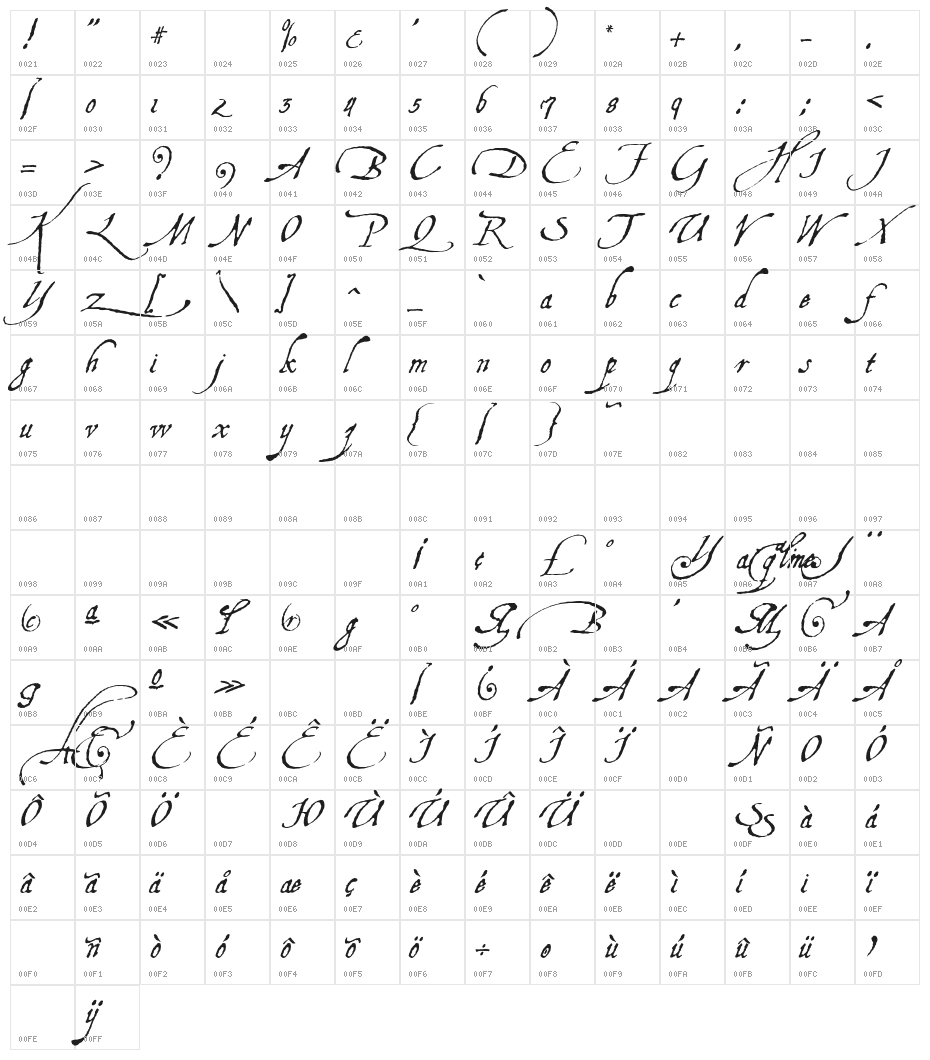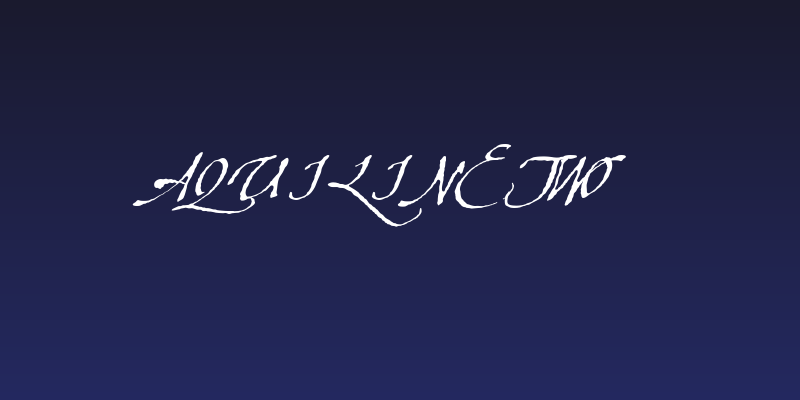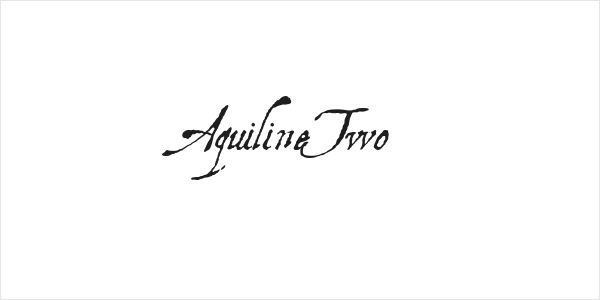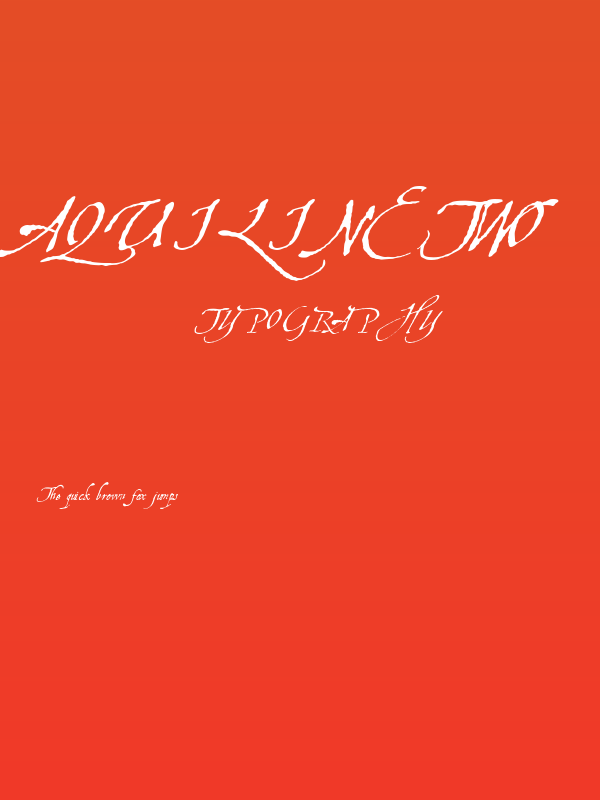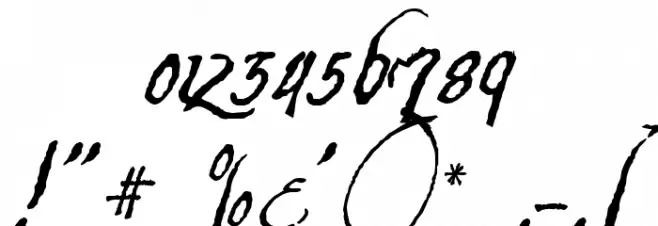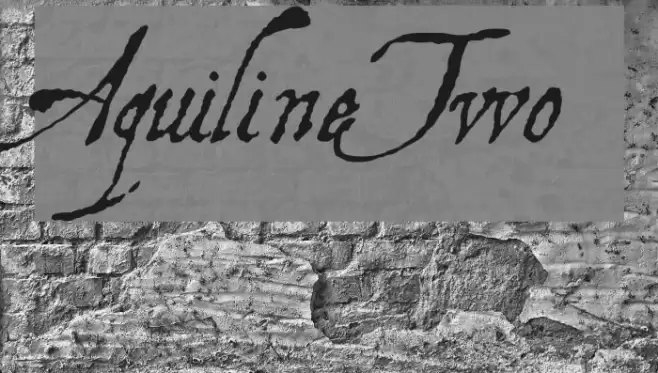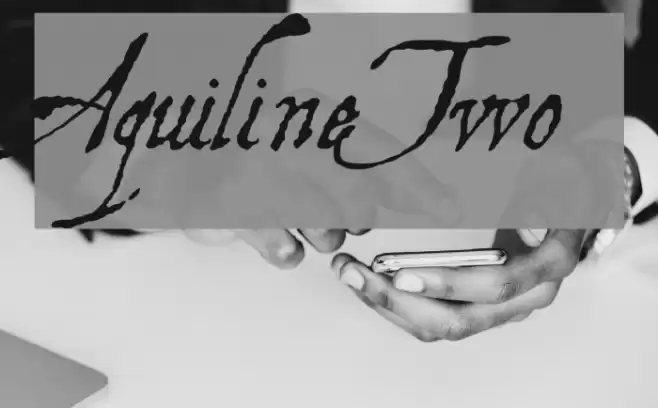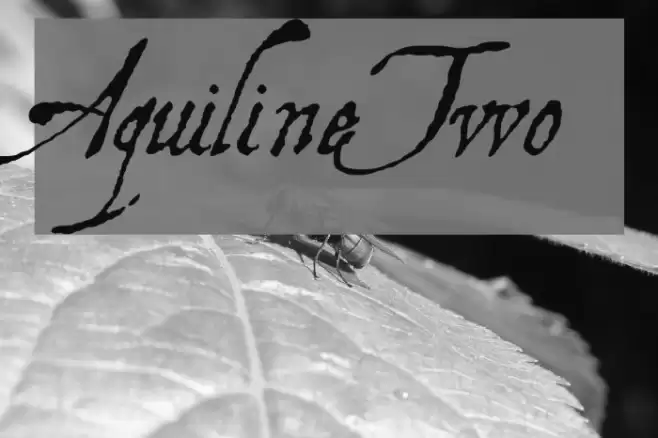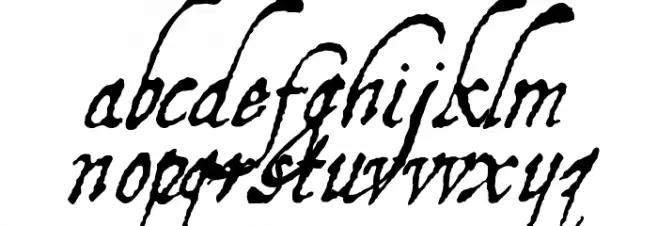
AquilineTwo Font
✎ Calligraphic
| Kategorien | Calligraphic |
| Gesamtstil | Elegant, Calligraphic |
| Anwendungsfall | Logos, Invitations, Decorative text |
| Vorgeschlagene Projekte | Ideal for wedding invitations, elegant branding, greeting cards, and decorative certificates. |